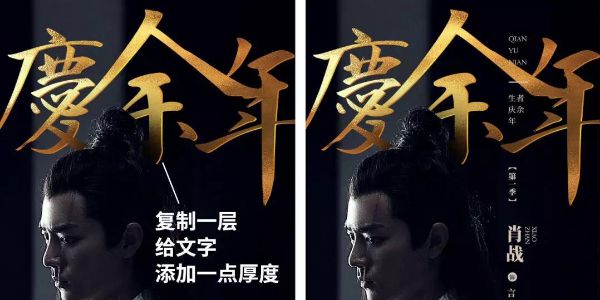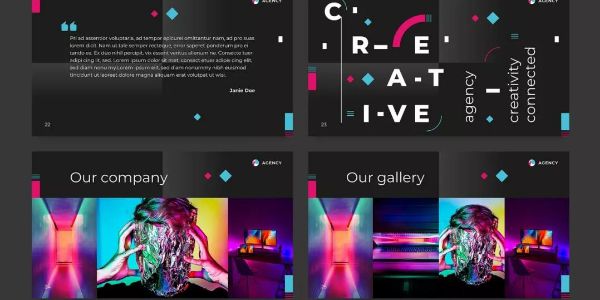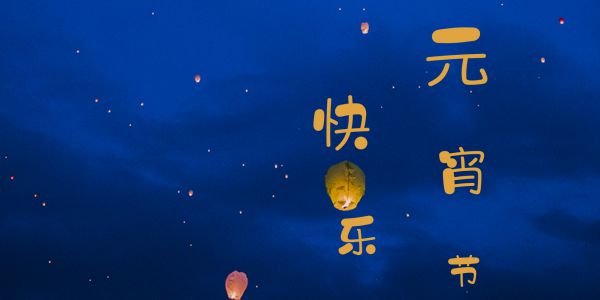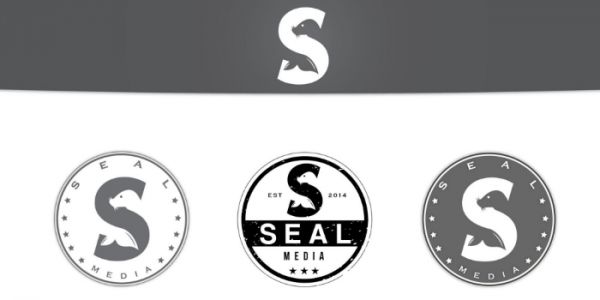
标题字的设计方法大全,100种标题文字的设计方法!
本来是想和小伙伴们分享8种标题字的设计方法的,又觉得8种完全不够设计师用呀?要不就15种吧!取个整数吧,20种。感觉20这个数字不太好,都没有20块钱的纸币了,算了取个整数...
分享100种标题文字的设计方法!!!操作比较复杂的附带视频教程。
说到文案吸引力,最佳的表现位置就是标题字。标题文字通常承载了海报的主题,需要通过大小、字体、色彩等方式突出呈现。很多设计师一味强调追求图具有吸引力,而忽略了文字的重要性。
1、高斯模糊
如图,这种文字高斯模糊,会给人一种远近的空间感!制作方法很简单:将文字图层转换成形状图层;菜单栏-窗口-属性-羽化值加大一些即可。
2、旋转模糊
这种模糊会给人一种眩晕的动感,将文字栅格化后执行滤镜-模糊-径向模糊即可。
3、文字变形
只要将文字合并成普通图层之后执行菜单栏-编辑-变换-变形即可。
或者使用液化工具涂抹。
4、字库造字
将文字图层右键转换成形状图层,修改其锚点,这种制作方法很考验字体设计的水平。
5、RGB分离
这种设计手法可以使标题变得非常迷幻。
菜单栏-图层-图层样式-混合选项-修改RGB通道即可呈现不同的色彩。
6、风格化
执行菜单栏-滤镜-风格化-风
7、文字切割
图中将“环境”切割成多个元素,意为被破坏的环境。我们只要用选区工具将文字切割成多个图层,并稍微错开位置即可。
8、叠加肌理
非常常用也非常简单的一种方法,找一个肌理素材剪切到文字中即可。
9、渐变叠加
这种设计方法一般都是背景颜色比较深时候使用,只要将文字分开后各自添加一个渐变的样式即可。
10、图文穿插
使用图层蒙版,可以快速制作图文穿插的效果,再添加一个阴影会更有感觉。
11、对齐
12、笔画模糊
将笔画复制出来添加羽化效果即可。
13、差集
这个方法不知道怎么命名,叫色彩反向?还是叫剪切,还是修剪,还是叫差集!反正镂空文字与图形相交的部分即可。
在AI里选中两个图形后,点击差集,或者复合路径,会将相交的地方镂空
14、文字变色
使用多种颜色,使得标题气氛更加活跃。
15、部首变色
使得标题更加活跃有趣。
16、字叠字
将主标题和次标题使用不同颜色或描边,叠加到一起。这样不仅会使得标题更有趣,还可以集中视觉焦点。
17、字型穿插
将文字和图形穿插,给人一种空间错觉,与图文穿插差不多。
18、部首换字
将部首替换成其他文字和字母,创意难,操作方法不难,只要将文字的笔画删除,添加其他文字或者字母即可。